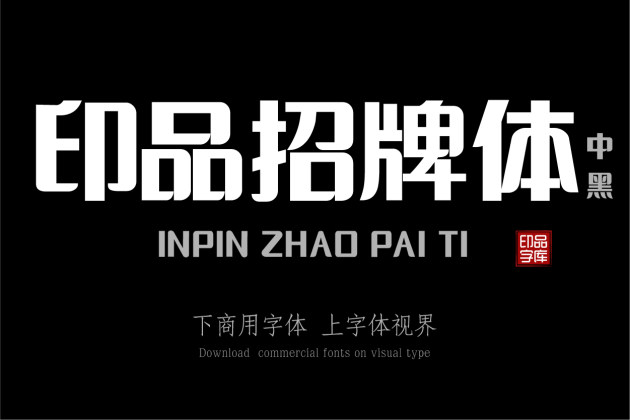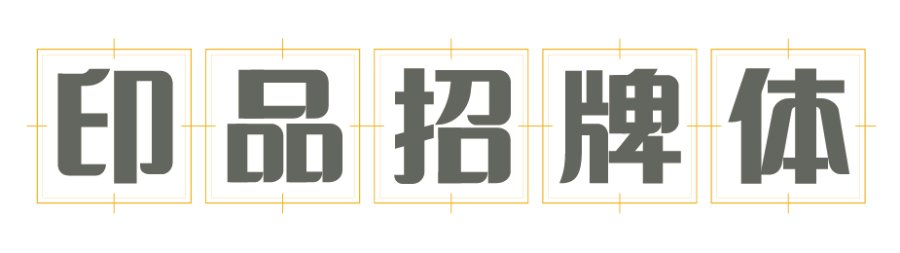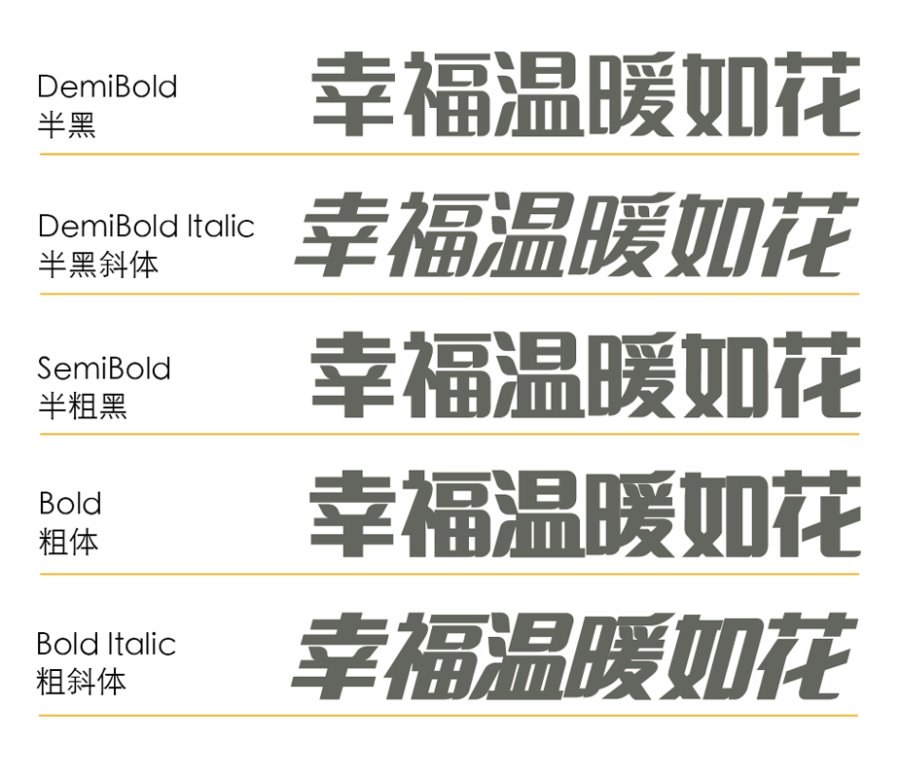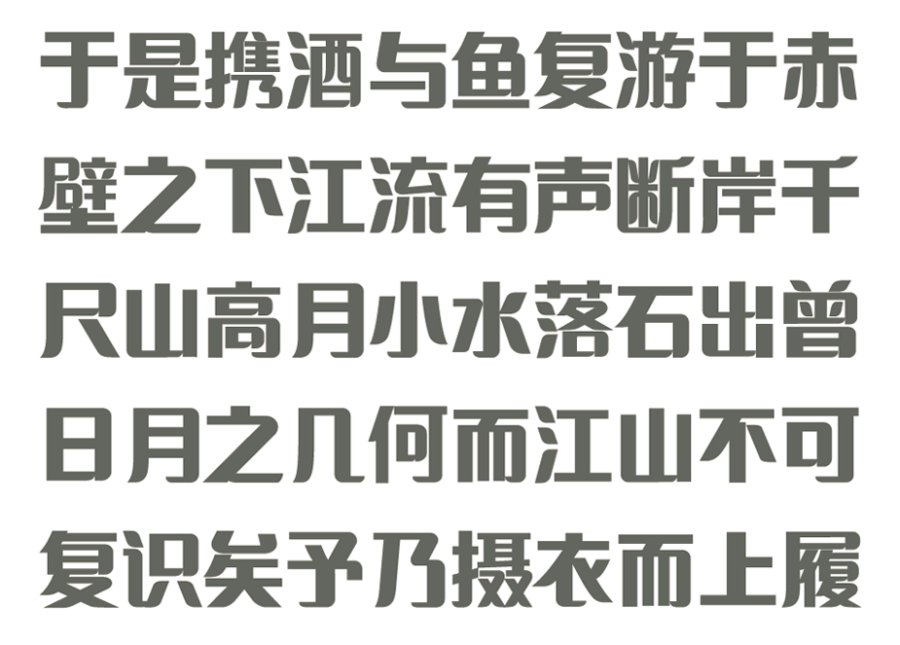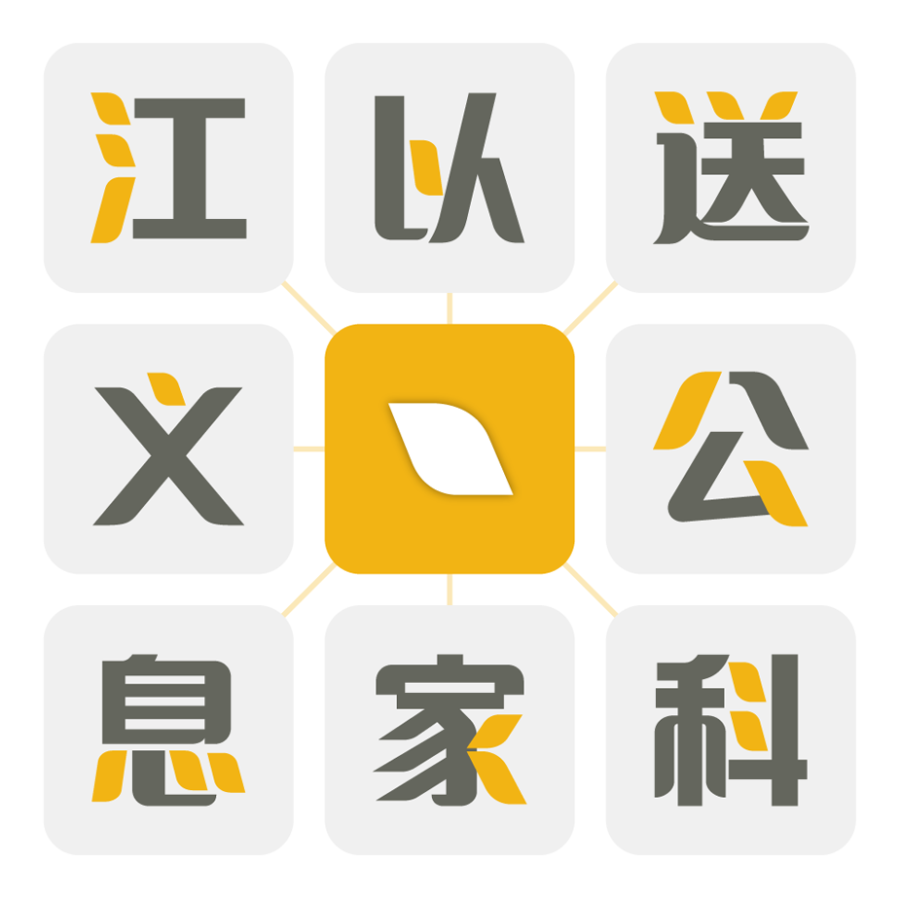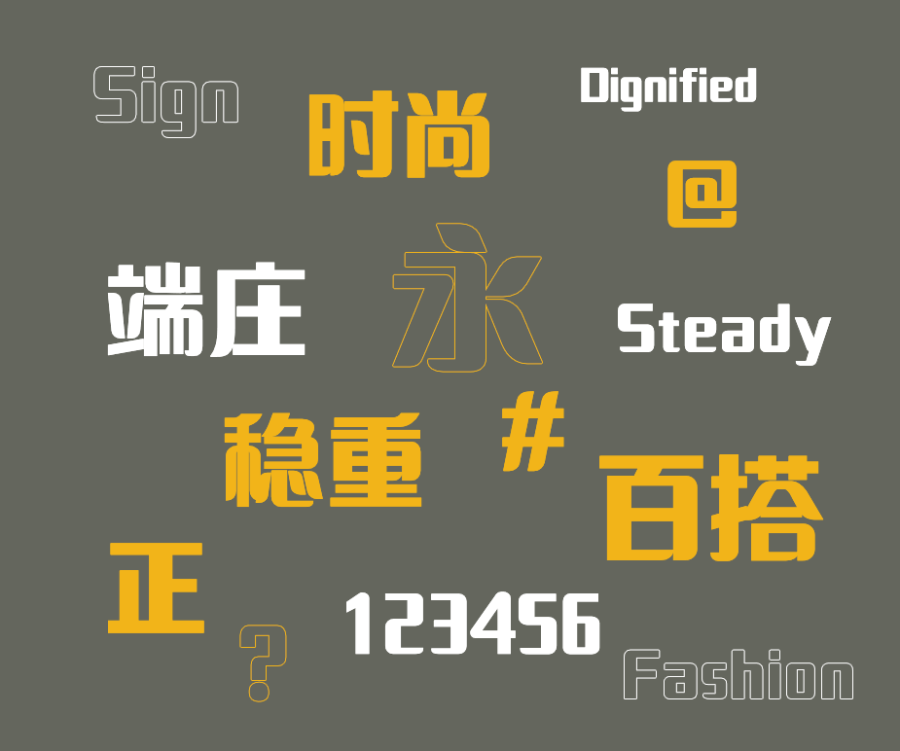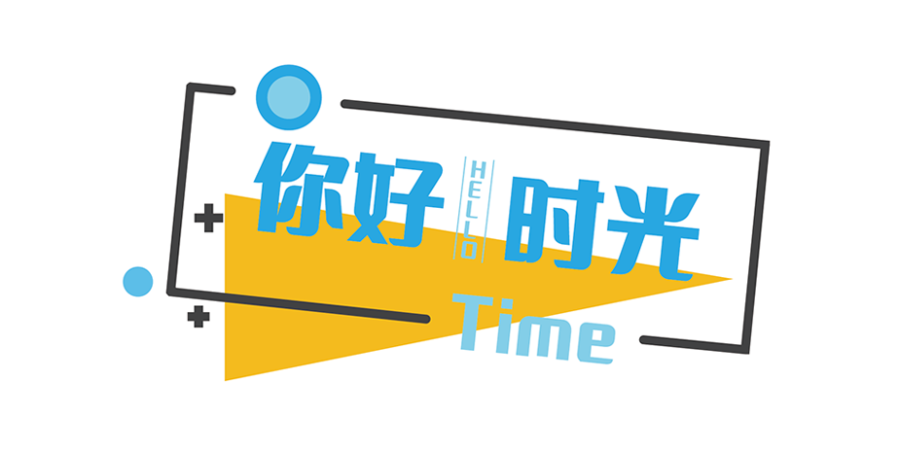
印品招牌体 中黑
这款招牌体字笔画粗壮,略带有纤细笔触,字形紧聚,但不失美感。在弯钩处都作了一点线条处理,看起来不那么死板。它的一撇一捺像极了柳絮飘飘。即便放于手机中阅读也不会产......
• 粗壮有力的黑体是被广泛使用的基本字体,不管是手机端还是电脑端基本上都是主流的屏显字体。 这款招牌体,相比于传统的黑体,更加圆润,让人感觉更加舒适。黑体字笔划整齐划一,它浑厚有力,朴素大方并且引人注目。 设计师在设计、做字过程中,做了一些细节调整优化。它的弯钩都作了一点线条处理,看起来不那么死板。它的一撇一捺像极了柳絮飘飘。这款字主要笔画粗壮,带有纤细笔触,字形紧聚,但不失美感。 设计师希望这款字体能被更多的人喜欢和使用。